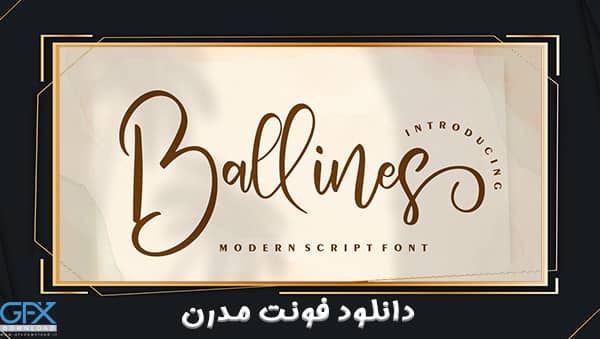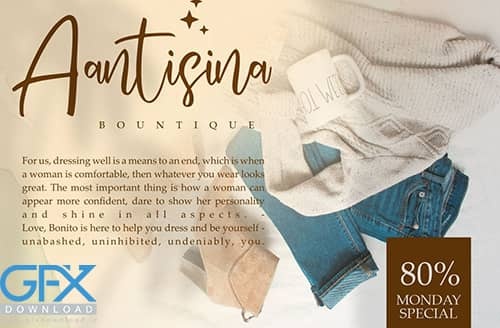
فونت رایگان مدرن Ballines
فونت مدرن Ballines
اسکریپت مدرن Ballines یک فونت جدید و بسیار زیبا است که برای بسیاری از نیازهای بصری شما مناسب است ، مانند دعوت نامه ، کارت تبریک ، برند تجاری ، کارت بیزنس ، نقل قول ها ، پوسترها و موارد دیگر! فونت رایگان مدرن Ballines دارای ویژگی پشتیبانی از چندزبانه است.